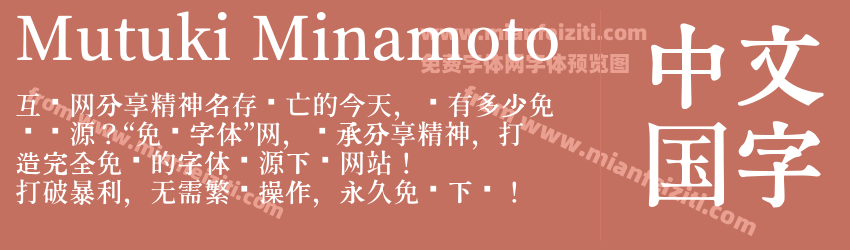
Mutuki Minamoto
字体名称: Mutuki Minamoto
Postscript名称: Mutuki-Minamoto
Mutuki Minamoto预览图1
Mutuki Minamoto预览图2
Mutuki Minamoto字体映射图
本款“Mutuki Minamoto”是一款书写很新颖的字体,字体大方,适合各种设计作品使用!欢迎下载!